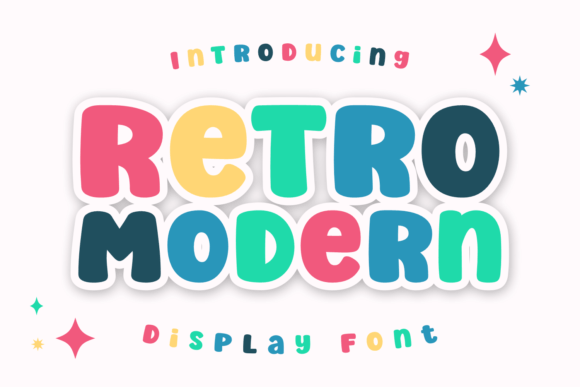
Retro Modern Font – مزيج مثالي بين الطابع الكلاسيكي واللمسة العصرية
اجعل تصاميمك تنبض بالأناقة والتميز مع Retro Modern Font، الخط الذي يجمع بين سحر الطراز القديم والأسلوب العصري المبتكر. يتميز هذا الخط بتفاصيله الأنيقة وحوافه الانسيابية، مما يجعله خيارًا مثاليًا لتصميم الشعارات، والعناوين، والتغليف، والمطبوعات، والمشاريع الرقمية.
✨ المميزات:
✔️ مزيج فريد بين الطراز الكلاسيكي والحديث
✔️ مثالي للعناوين والشعارات والتصميمات الإبداعية
أضف لمسة من الإبداع إلى أعمالك مع Retro Modern Font، واجعل تصاميمك تبرز بجاذبية استثنائية! ????????